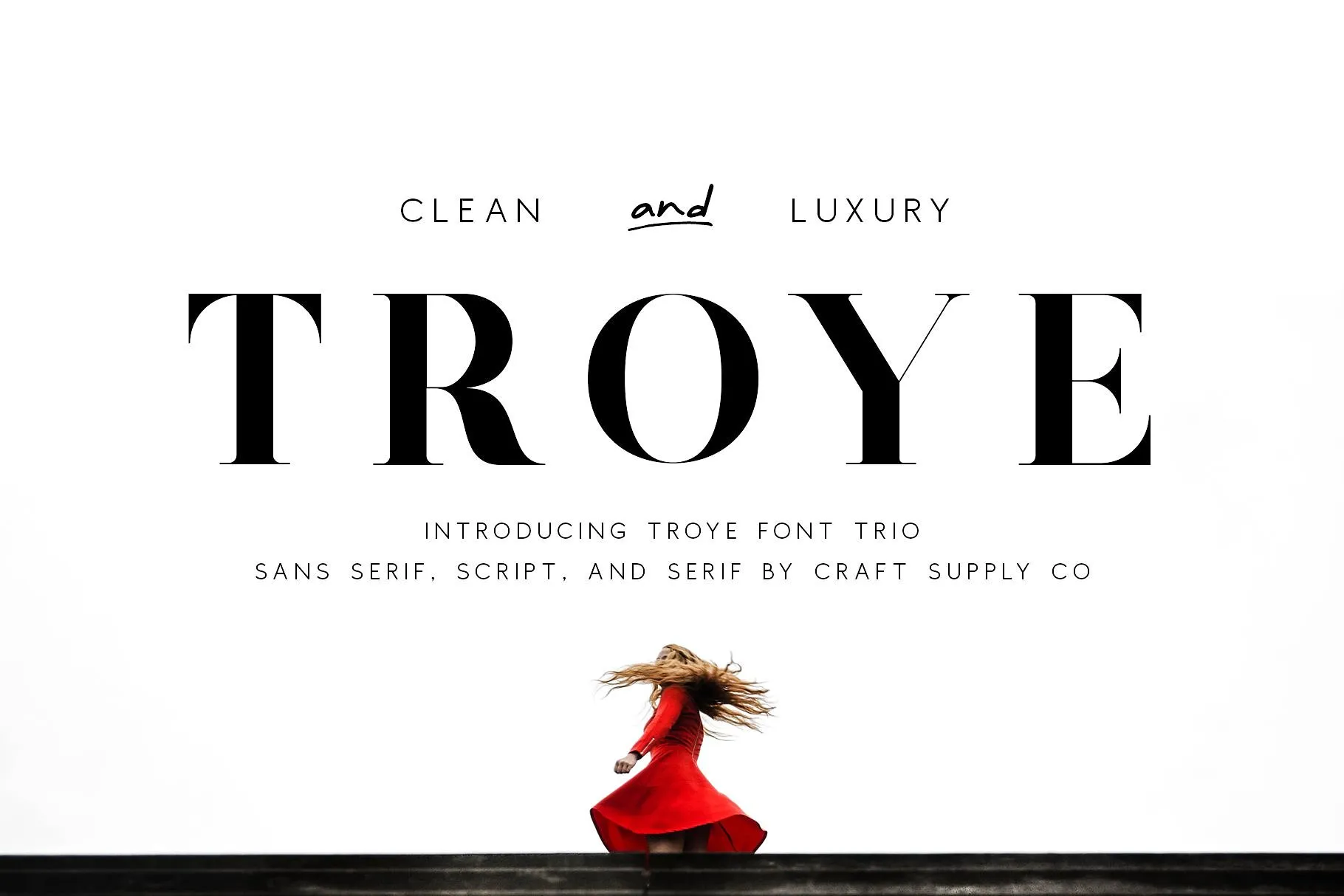
Troye Font Trio – Download Grátis
A font Troye Font Trio é uma escolha perfeita para designers que desejam criar projetos visuais modernos com elegância. Inspirada na combinação entre a paixão, a calma e o equilíbrio, essa trilogia de tipos de letra combina script, sans-serif e serif em um design gráfico sofisticado. Através de seu design leve, cheio de charme e elegância, você pode personalizar sua identidade visual para projetos como logotipos de fotografias, assinaturas, capas de álbuns, cartões de visita e muito mais. Esta font é especialmente adequada para aplicações como água-marinha em fotografias ou assinaturas. Não perca esta oportunidade de trazer uma pitada de elegância para seus projetos design. Através da Troye Font Trio, você pode experimentar o máximo do seu potencial criativo!